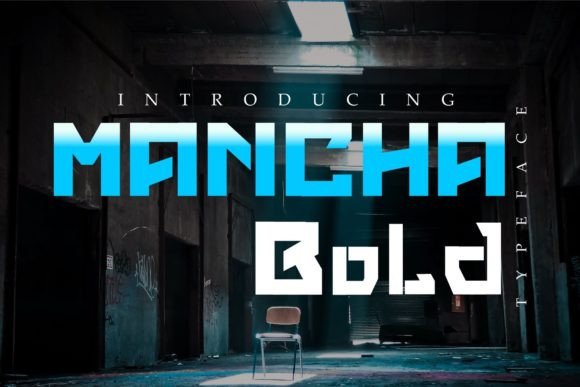
Mancha Bold
Mancha Bold – La police d’affichage moderne qui dynamise vos créations
Si vous cherchez une typographie à la fois moderne et ludique pour vos projets de design, Mancha Bold de Kong Font Studio est la solution idéale. Cette police d’affichage se démarque par son style cool et sa grande lisibilité, ce qui la rend parfaite pour les crafters, les graphistes et les créateurs de contenus digitaux.
Voici les points forts qui font de Mancha Bold un incontournable dans votre boîte à outils créative :
- Design moderne et audacieux : des formes géométriques et des contrastes forts qui captent immédiatement l’attention.
- Polyvalence d’utilisation : idéale pour les titres, les logos, les affiches, les invitations et même les projets de découpe laser.
- Aspect ludique qui ajoute une touche de créativité et de personnalité à chaque projet.
Grâce à son style distinctif, Mancha Bold se prête particulièrement bien aux projets suivants :
- Cartes de vœux et invitations personnalisées.
- Logotypes de marques jeunes et dynamiques.
- Affiches d’événements culturels ou festifs.
- Designs de produits Cricut ou Silhouette pour le DIY.
- Visuels pour les réseaux sociaux qui se démarquent dans le fil d’actualité.
En résumé, Mancha Bold est une police d’affichage moderne, cool et ludique qui répond aux exigences des créateurs actuels. Que vous soyez un designer professionnel ou un amateur passionné, cette police vous aidera à donner du caractère à vos projets tout en restant facile à manipuler dans vos outils préférés.